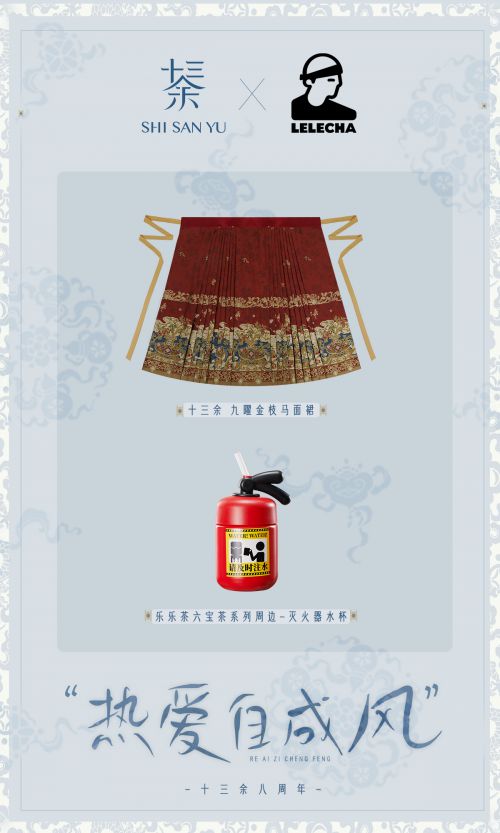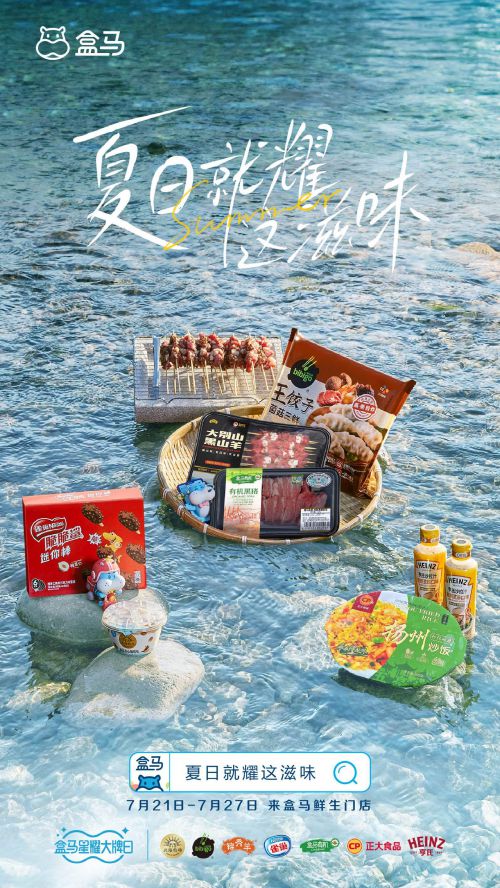
鸿雷拙书简体
【鸿雷拙书简体】是由鸿雷字记推出的手写体字体,支持免费商用授权,以粗犷手写风格为设计核心。字体字形方正稳健,字体重心居中,中宫宽博舒展,展现出从容大气的视觉张力。笔型采用独特斜切设计,方头笔画搭配均匀粗细的线条,既保留手写书法的自然笔触,又通过断开式笔画结构增强设计感。 鸿雷拙书简体兼具手写温度与设计张力,粗重笔触传递出质朴力量,方正结构确保排版稳定,适用于海报标题、产品包装、自媒体配图等多元场景。常规字符集覆盖日常用字需求,免费商用属性更降低商业设计门槛,是手写风设计的实用之选。其将传统书法韵味与现代设计需求融合,以拙朴笔触构建出兼具识别性与艺术性的文字美学。